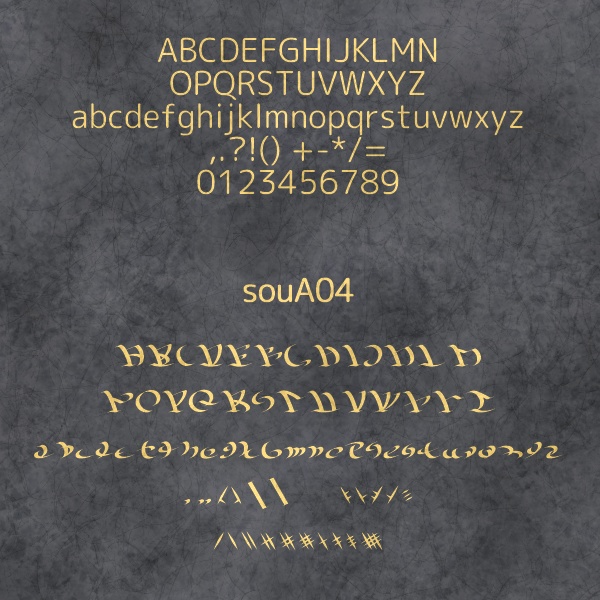
異国語・呪文フォント「souA04」
CLIP STUDIO ASSETSで配布している 「文字ブラシ6」(https://assets.clip-studio.com/ja-jp/detail?id=1777482)を フォント化したものです。 アルファベットをベースにアレンジした、未知の言語っぽい文字列を 作成するためのフォント(OpenTypeフォント)です。 通常より甘い作りなので緩い心持でお使いください。 【注意事項】 著作権は放棄しておりません。 意匠・商標登録などに使用することはご遠慮ください。 フォントデータの販売・再配布もご遠慮ください。 その他の使用についてはご自由に。 また、当フォントの使用により損害などが生じても、 一切の責任を負いませんのでご了承ください。 【タイプ可能な文字】 ABCDEFGHIJKLMNOPQRSTUVWXYZ abcdefghijklmnopqrstuvwxyz 0123456789,.?!()+-*/=